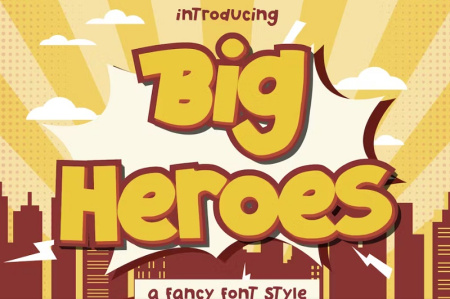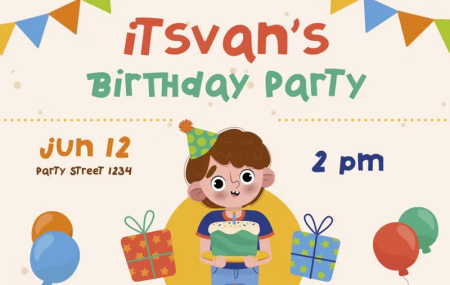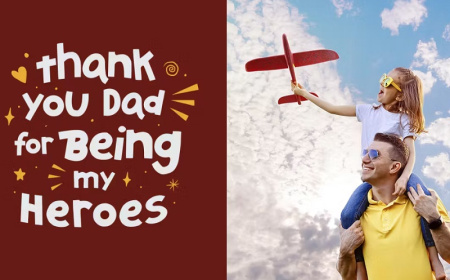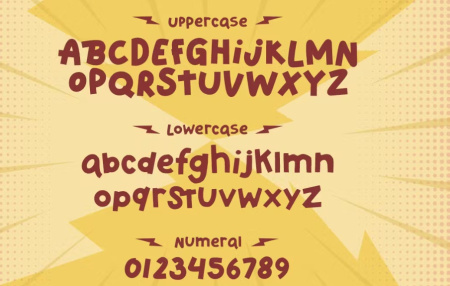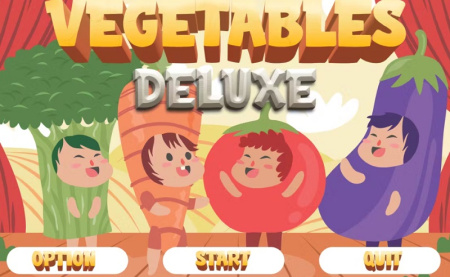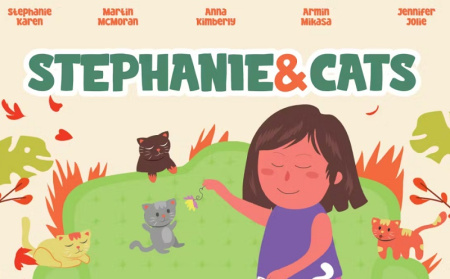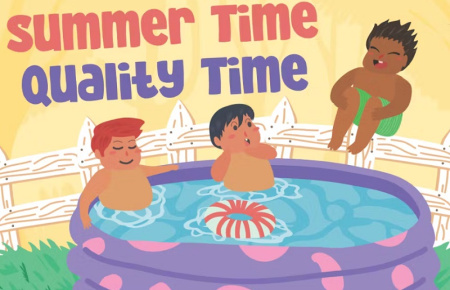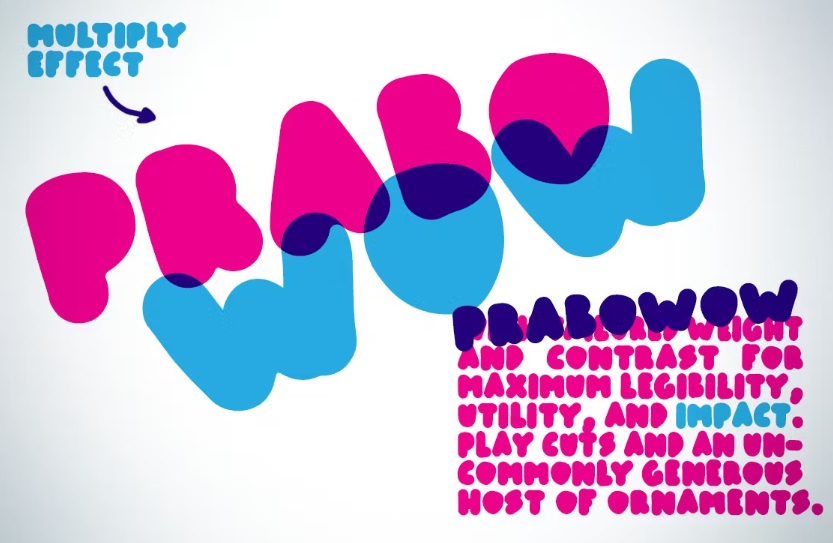
3 فونت انگلیسی چاق Big Heroes
فونت انگلیسی چاق
فونت انگلیسی چاق شامل 3 فونت انگلیسی زیبا با طراحی چاق و بزرگ می باشد. این فونت ها شادی زیادی را برای طراحی های شما به ارمغان می آورد. مناسب برای بازار بچه ها، بازی های آنلاین، نوشت افزار، تی شرت و فونت وسایل مدرسه، پوستر، عنوان فیلم، جلدهای یوتیوب، تصاویر کوچک یوتیوب، جلد صفحه رسانه های اجتماعی و غیره...
همچنین با دانلود فونت انگلیسی چاق از سایت gfx از آنها می توانید برای سرفصل‌ها، بروشورها، کارت‌های تبریک، بسته‌بندی محصول، جلد کتاب، نقل قول‌های چاپی، لوگوتایپ، جلد آلبوم و غیره استفاده کنید.
این فونت چاق و تپل انگلیسی برای عنوان یا هر طراحی دیگر مناسب است. فونت انگلیسی چاق یک فونت فوق العاده زیبا است که می‌توان از آن در طراحی انواع پوستر، بنر، بروشور، بسته بندی محصولات، چاپ و سایر طراحی ها استفاده کرد.
✅ نام فونت انگلیسی1: Big Heroes
✅ نام فونت انگلیسی2: Big Jano
✅ نام فونت انگلیسی3: Prabo Fat font